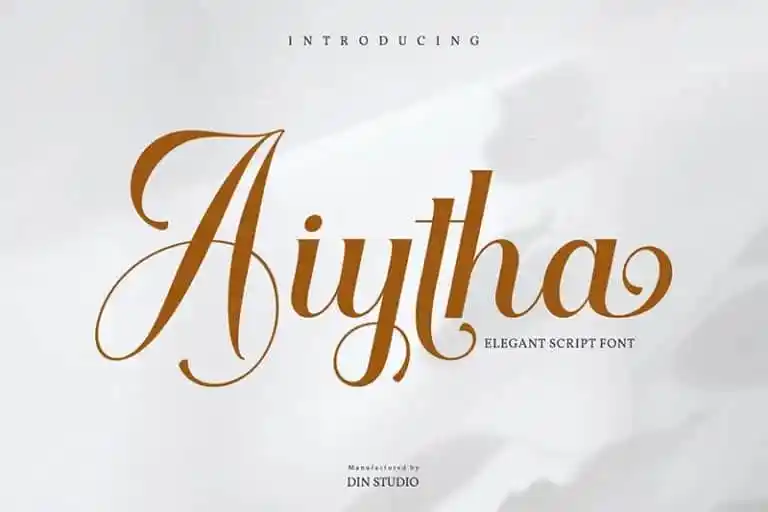
Aiytha Calligraphy Font – Fonte Grátis
Aiytha Calligraphy Font
Aiytha Calligraphy Font é uma elegante fonte de tipo script que pode ser usada para qualquer projeto, desde logomarcas até designs de roupas e decoração. Ela se tornou um recurso indispensável para designers profissionais, especialmente em tarefas como criação de logotipos ou mensagens de casamento. Sua sofisticação moderna não perde o charme e a delicadeza típica da escrita por arte. Criada pela Din Studio, esta fonte traz uma aposta segura para qualquer projeto que exija um toque sofisticado e elegante no design gráfico. Seja para criar um logotipo impecável ou formar uma mensagem emocionalmente forte, a Aiytha Calligraphy Font é definitivamente o melhor amigo de profissionais em busca de uma fonte de tipo à altura.